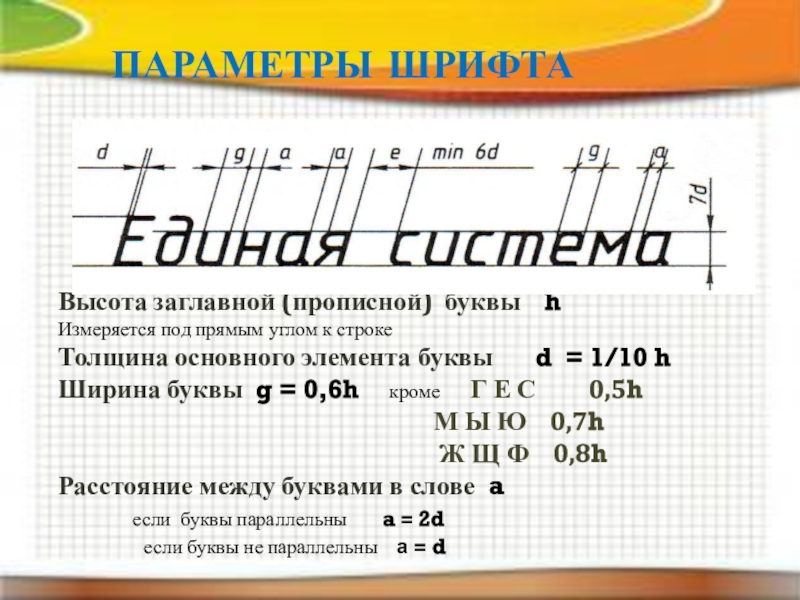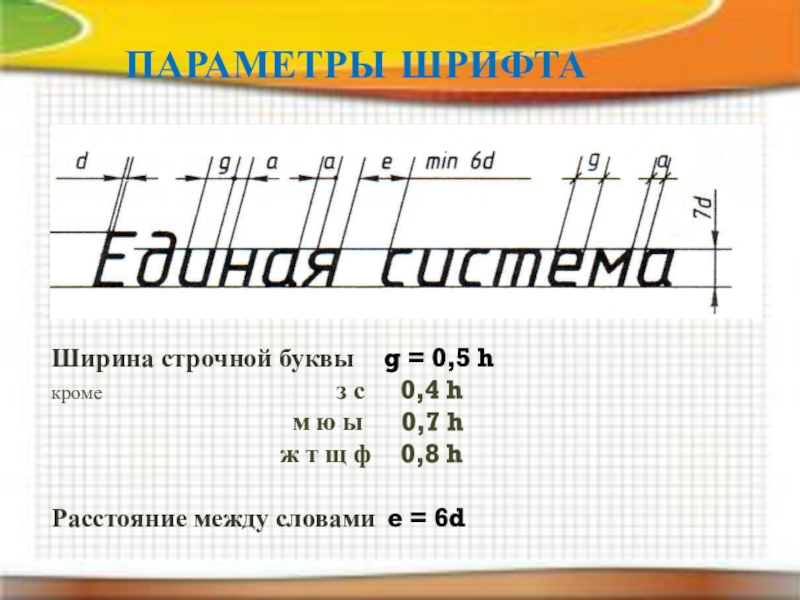
Впервые в России
ввел Петр I в 1709 годудля выполнения надписей на чертежах.
Современный шрифт установлен
ГОСТом 2.304-82
для оформления чертежей и другой текстовой документации
во всех отраслях промышленности